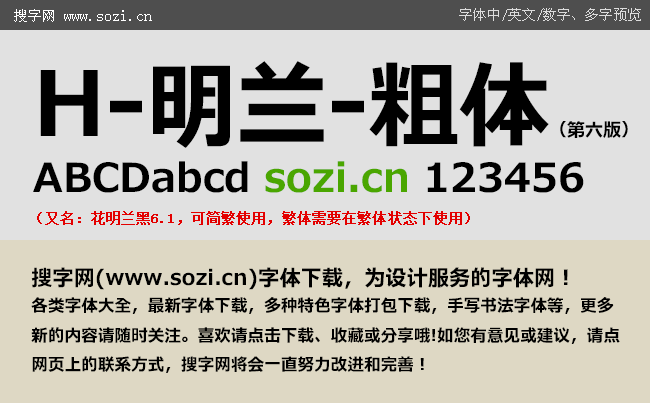
花明蘭黑6.1-粗體
搜字網(wǎng)提供一款花明蘭黑6.1-粗體中文字體下載,花明蘭黑6.1-粗體是一款非常端正的黑體字體,字體端正大方,簡(jiǎn)潔易讀,十分醒目,適合廣告設(shè)計(jì)、畫(huà)冊(cè)排版、包裝設(shè)計(jì)等設(shè)計(jì)場(chǎng)合使用。
• 風(fēng)格類(lèi)別: 黑體